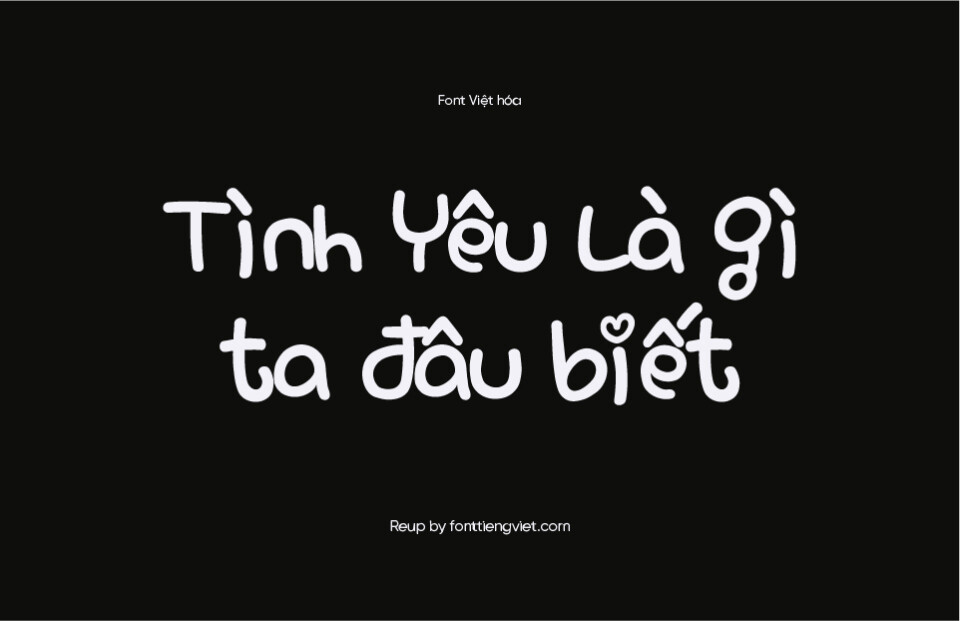
Font Việt hóa Rix Love Fool – RixLoveFool – Font cho Valentine
Font Việt hóa Rix Love Fool – RixLoveFool – Font cho Valentine – Lựa chọn ngọt ngào cho thiết kế tình yêu
Giới thiệu về Font Việt hóa Rix Love Fool – RixLoveFool – Font cho Valentine
Trong thế giới sáng tạo, việc tìm kiếm một bộ Font Miễn Phí mang đậm hơi thở lãng mạn là điều vô cùng cần thiết cho các nhà thiết kế. Font Việt hóa Rix Love Fool – RixLoveFool – Font cho Valentine nổi lên như một biểu tượng của sự ngọt ngào và trẻ trung. Đây là bộ font chữ đặc biệt, được thiết kế với những đường nét mềm mại, phá cách, giúp truyền tải thông điệp yêu thương một cách trọn vẹn nhất. Với sự hỗ trợ đầy đủ các ký tự tiếng Việt, bộ font này loại bỏ hoàn toàn nỗi lo lỗi font khi gõ dấu, mang lại trải nghiệm mượt mà cho người dùng.
Đặc điểm nổi bật của Font Việt hóa Rix Love Fool – RixLoveFool – Font cho Valentine
Phong cách thiết kế độc đáo
Bộ Font Việt hóa Rix Love Fool – RixLoveFool – Font cho Valentine sở hữu cấu trúc chữ viết tay tự nhiên, tạo cảm giác gần gũi và chân thật. Các nét chữ được uốn lượn tinh tế, mô phỏng lại những lá thư tình đầy cảm xúc, rất phù hợp cho các dự án nghệ thuật dành cho giới trẻ.
Ứng dụng đa dạng trong thực tế
Không chỉ giới hạn trong các tấm thiệp mừng, font chữ này còn cực kỳ hiệu quả khi làm tiêu đề video, ảnh bìa mạng xã hội hay các ấn phẩm quảng cáo cho mùa lễ hội. Sự linh hoạt giúp nó trở thành lựa chọn hàng đầu cho các bạn học sinh khi làm báo tường hoặc trang trí bài học.
Tại sao nên tải Font Việt hóa Rix Love Fool – RixLoveFool – Font cho Valentine?